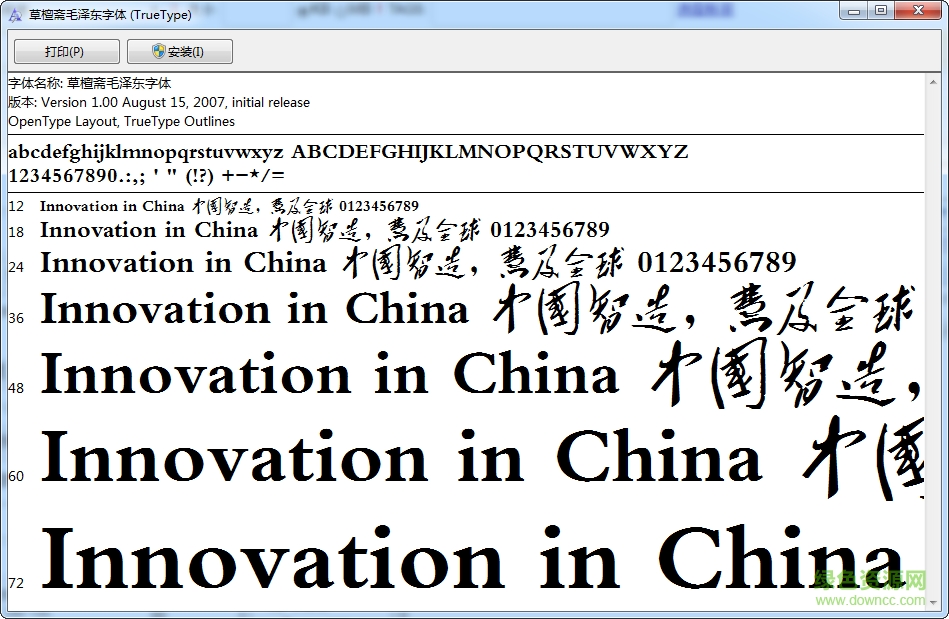
毛体书法字体
毛体字体是一款以伟大无产阶级革命家毛泽东同志的手写字体研发而来,字形有气势、有力度、有神韵,生动活泼,柔韧雄强,彰显了中华民族精神,有喜欢的朋友赶紧来绿色资源网下载使用!
毛体字体简介
毛体字体是以高清晰《毛泽东书古诗词手迹》,《题词系列手迹》为基础开发的,集手稿字一万两千余个,字体整体风格统一。集众美于一体,有丰富的美学内涵,达到很高的艺术境界。